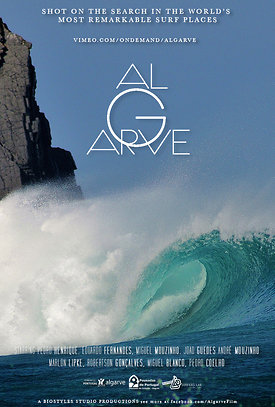
Suche diese dünne Schriftart!
Ich hoffe, mir kann jemand sagen, welche Schriftart das im angehängten Bild ist...
Das R könnte der Avant Garde Gothic Extra Light entspringen …  :-?